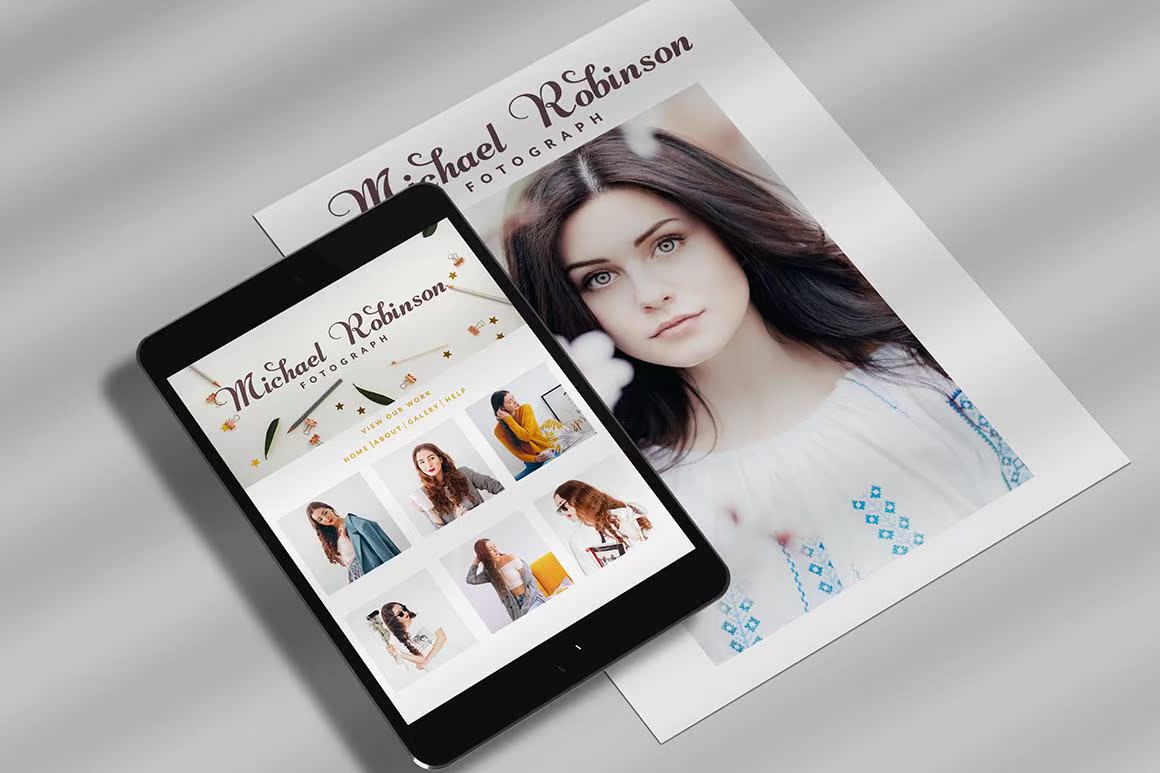
Sinami是一款别致的手写字体。经验证的纹理是一款完美的选择。它是一款粗体的经典AlligraphyLookmaking,适用于品牌和数字设计、徽标、邀请函、名片、web、instagram、社交媒体、报价、印刷品、墙饰、品牌项目等!Sinami是一款别致的手写字体。经验证的纹理是一款完美的选择。它是一款粗体的经典AlligraphyLookmaking,适用于品牌和数字设计、徽标、邀请函、名片、web、instagram、社交媒体、报价、印刷品、墙饰、品牌项目等!